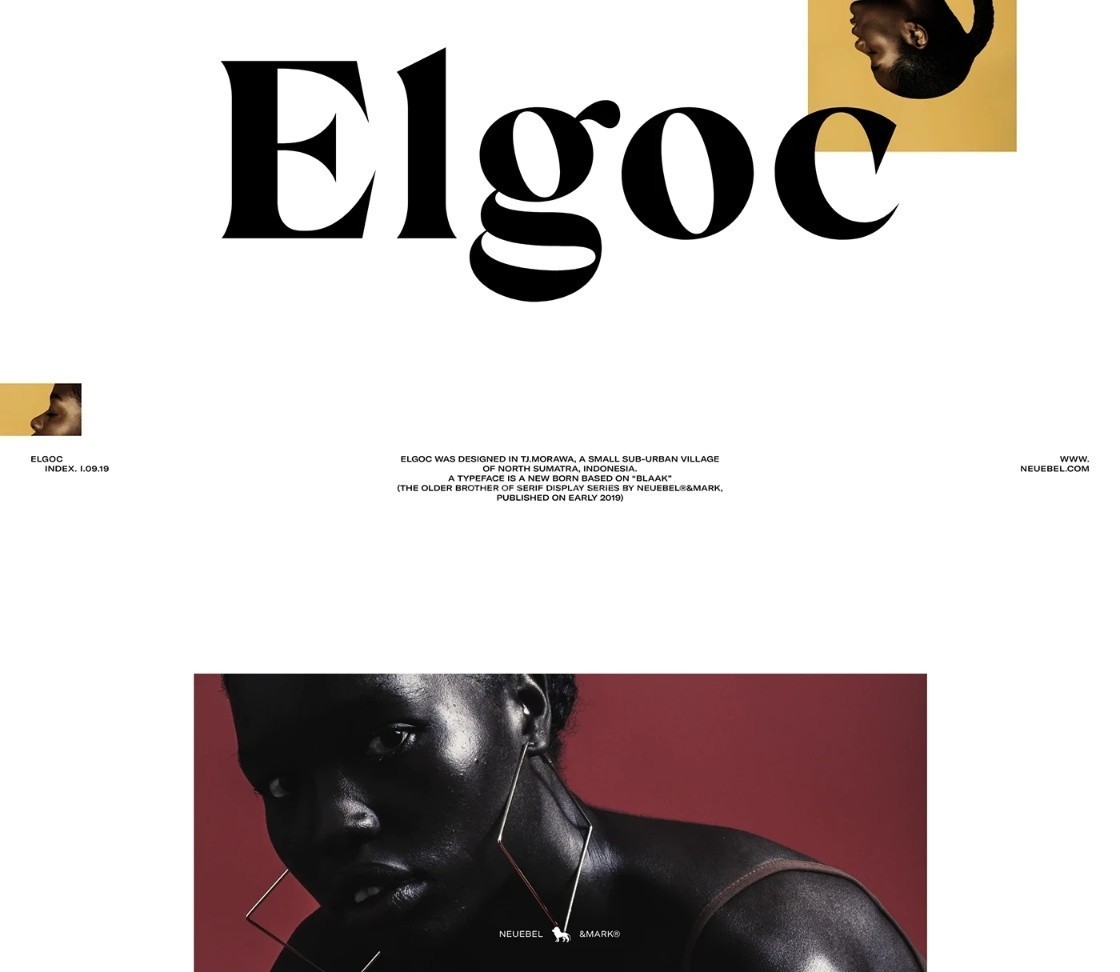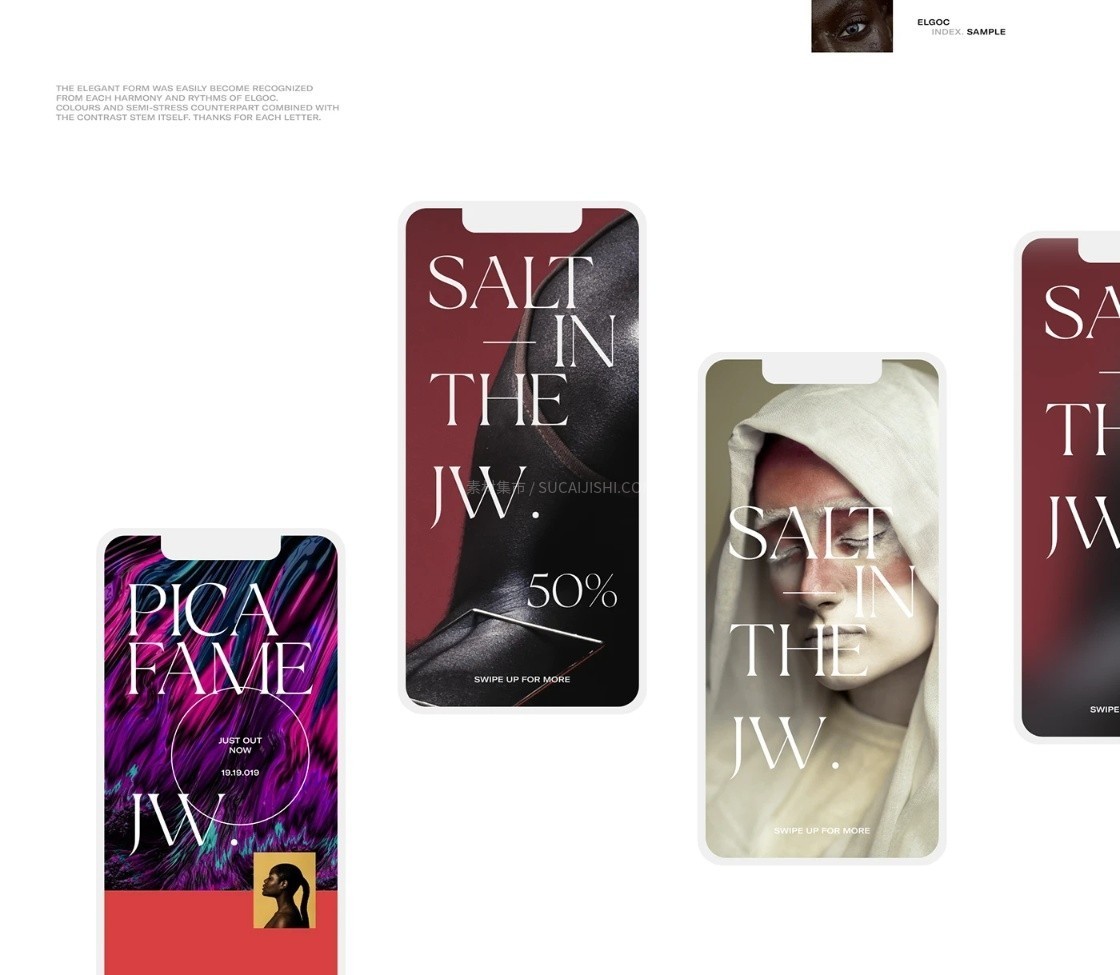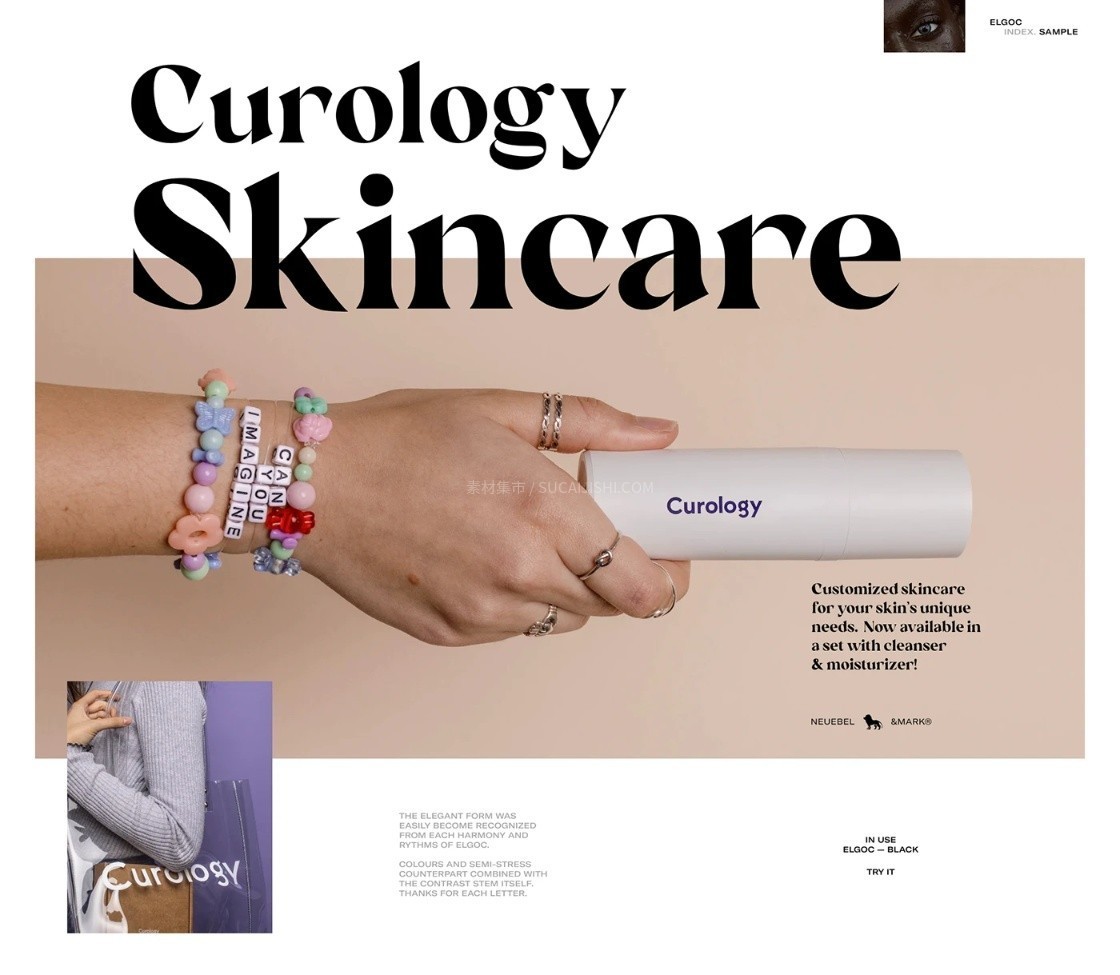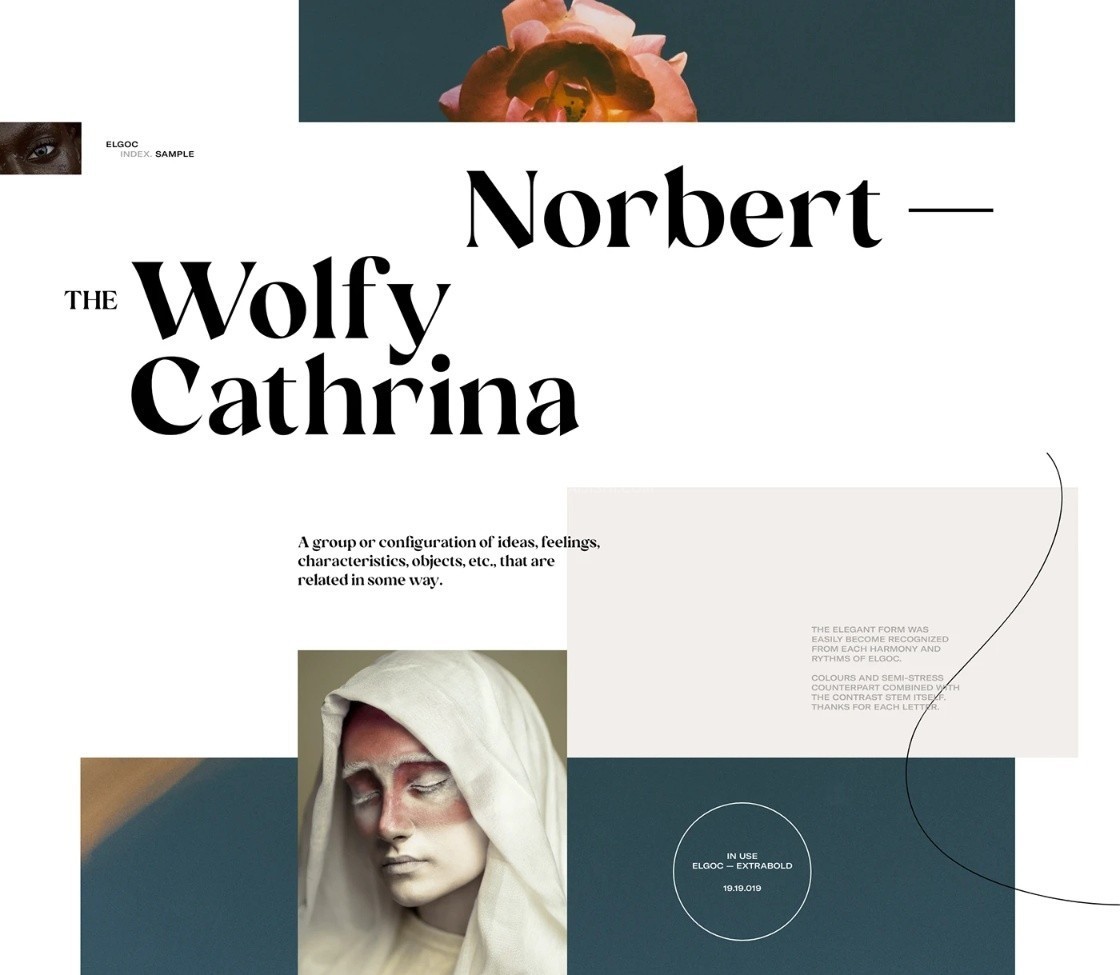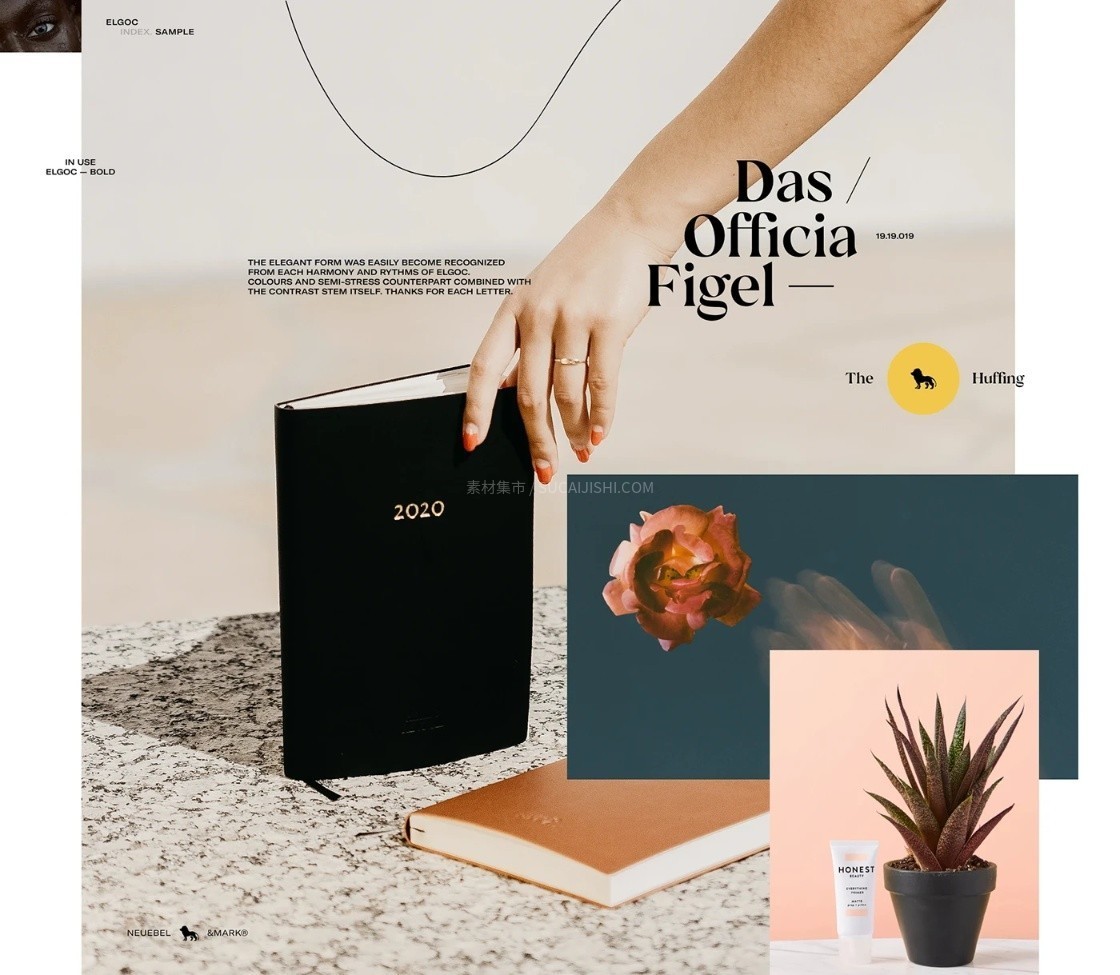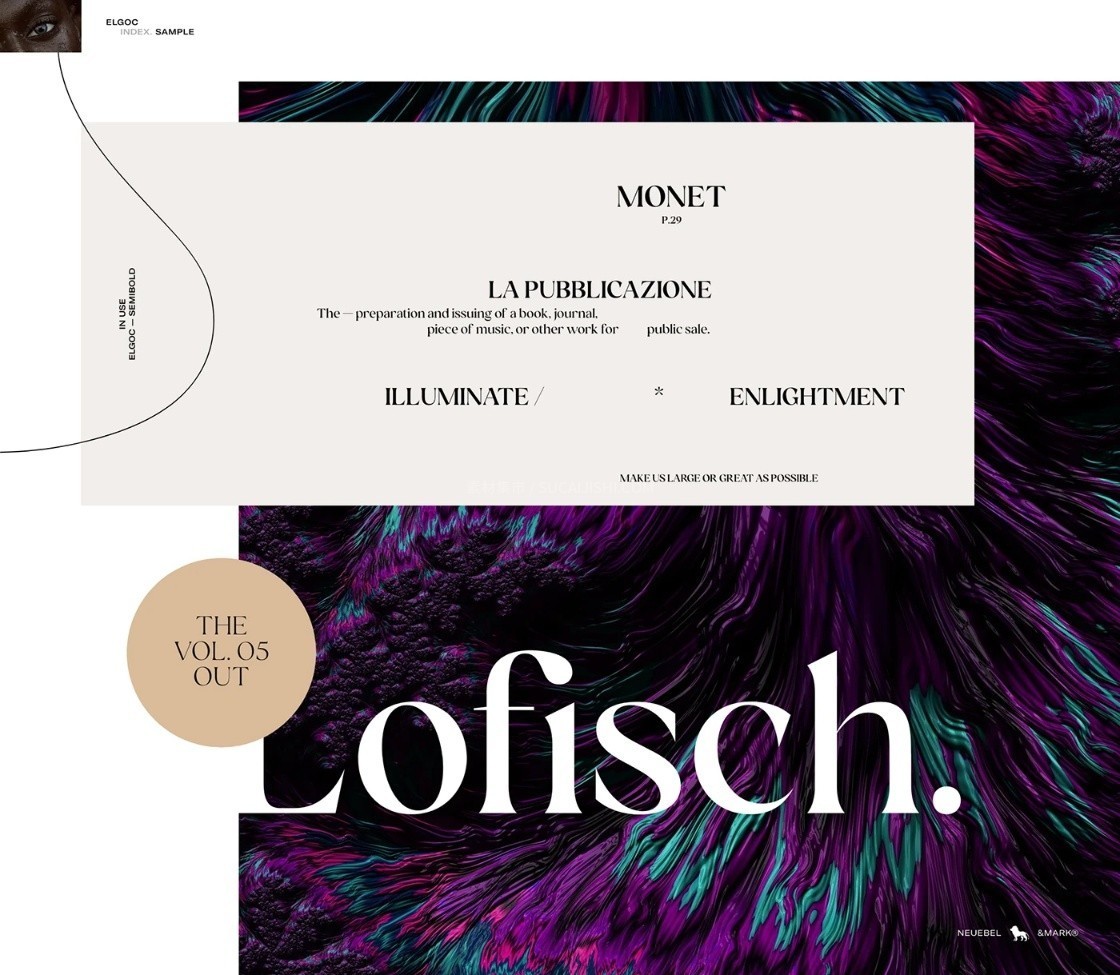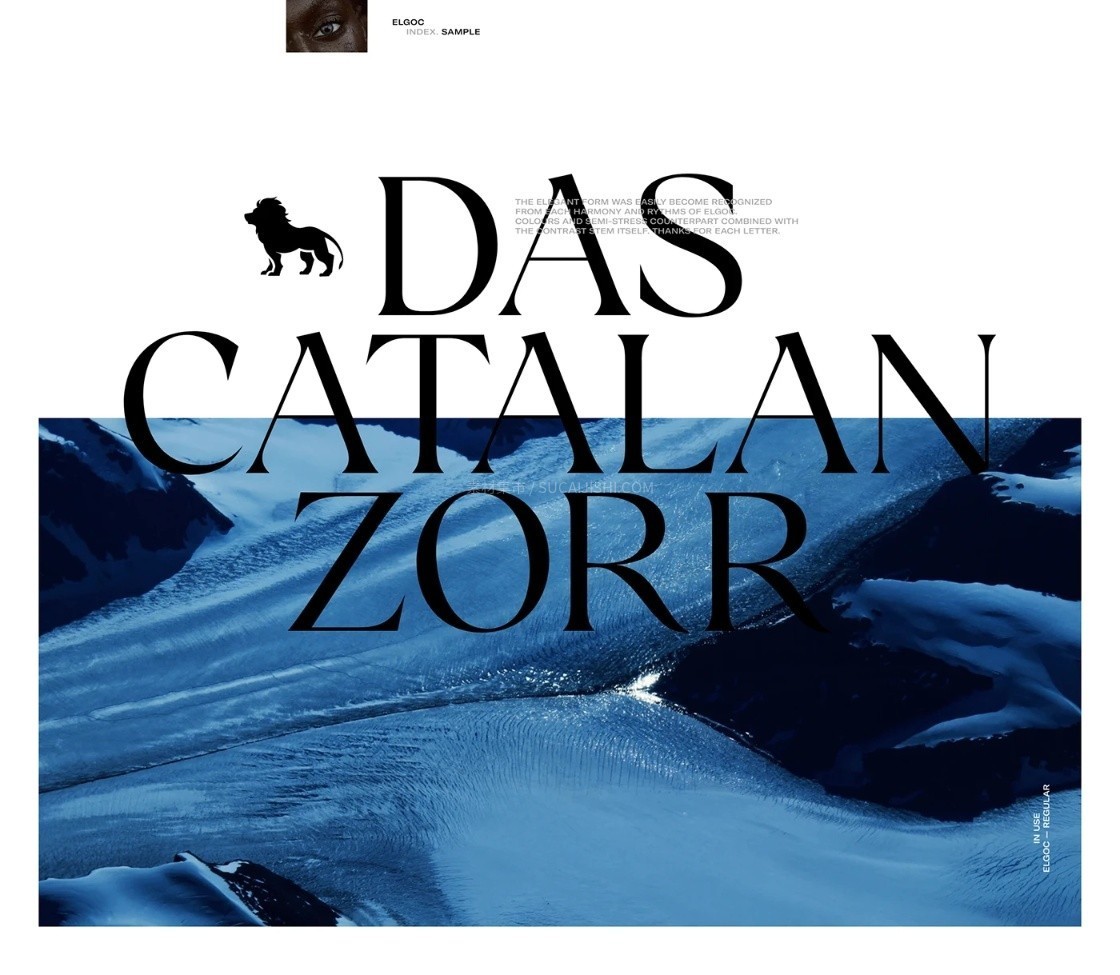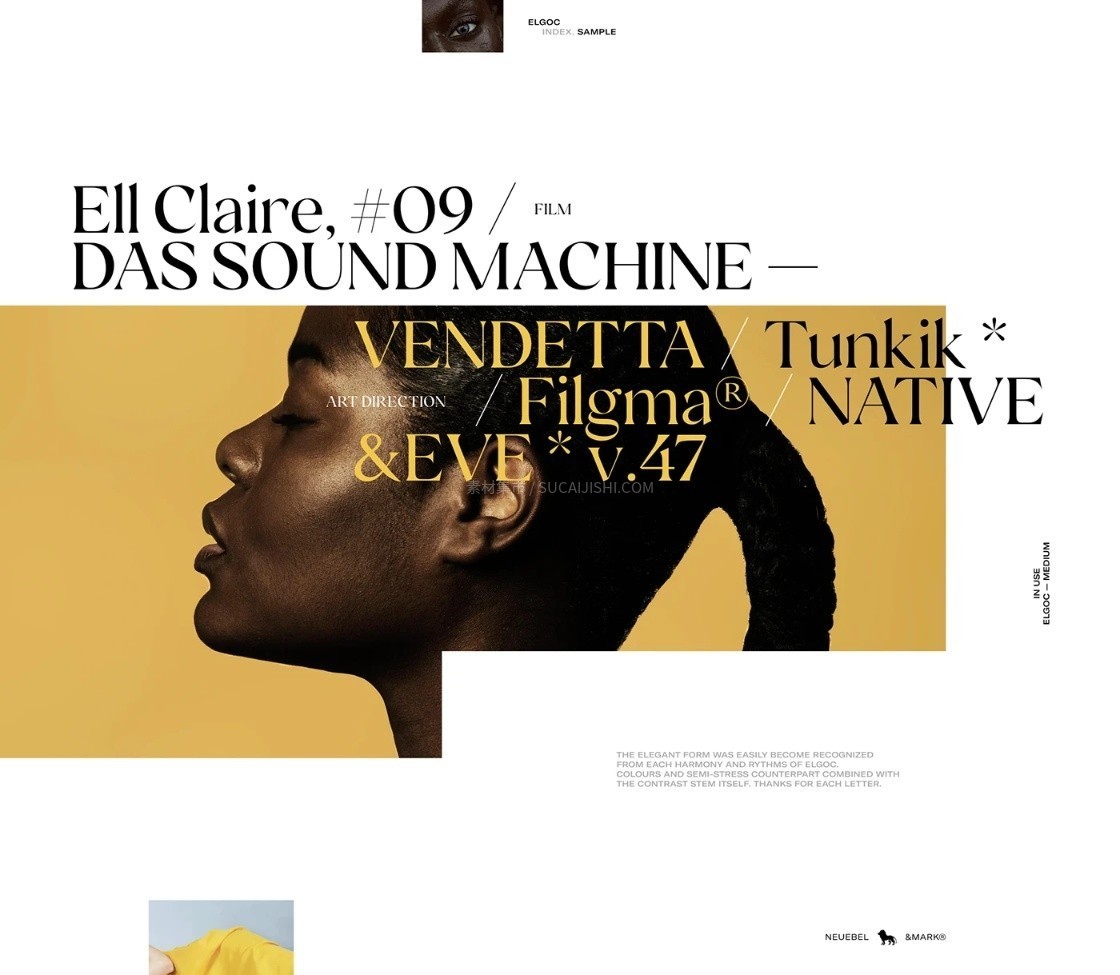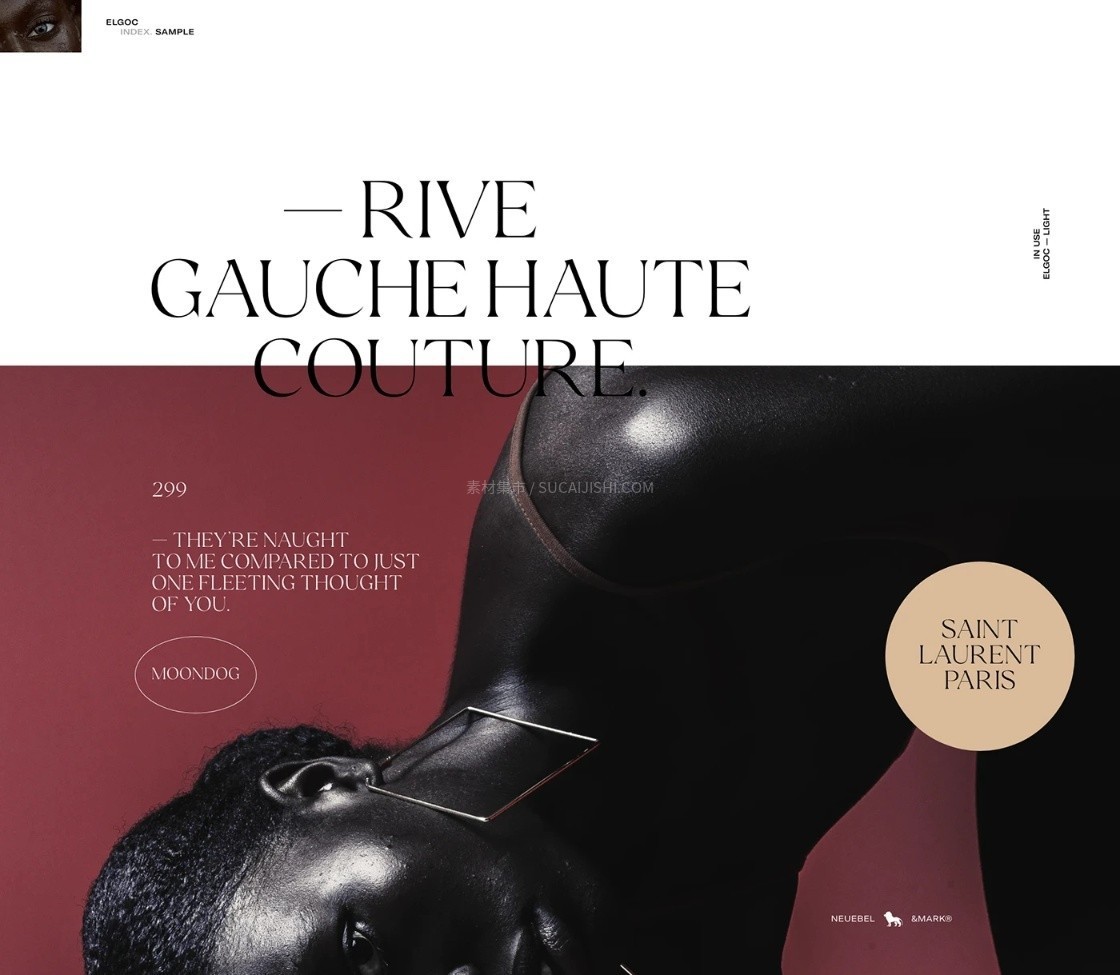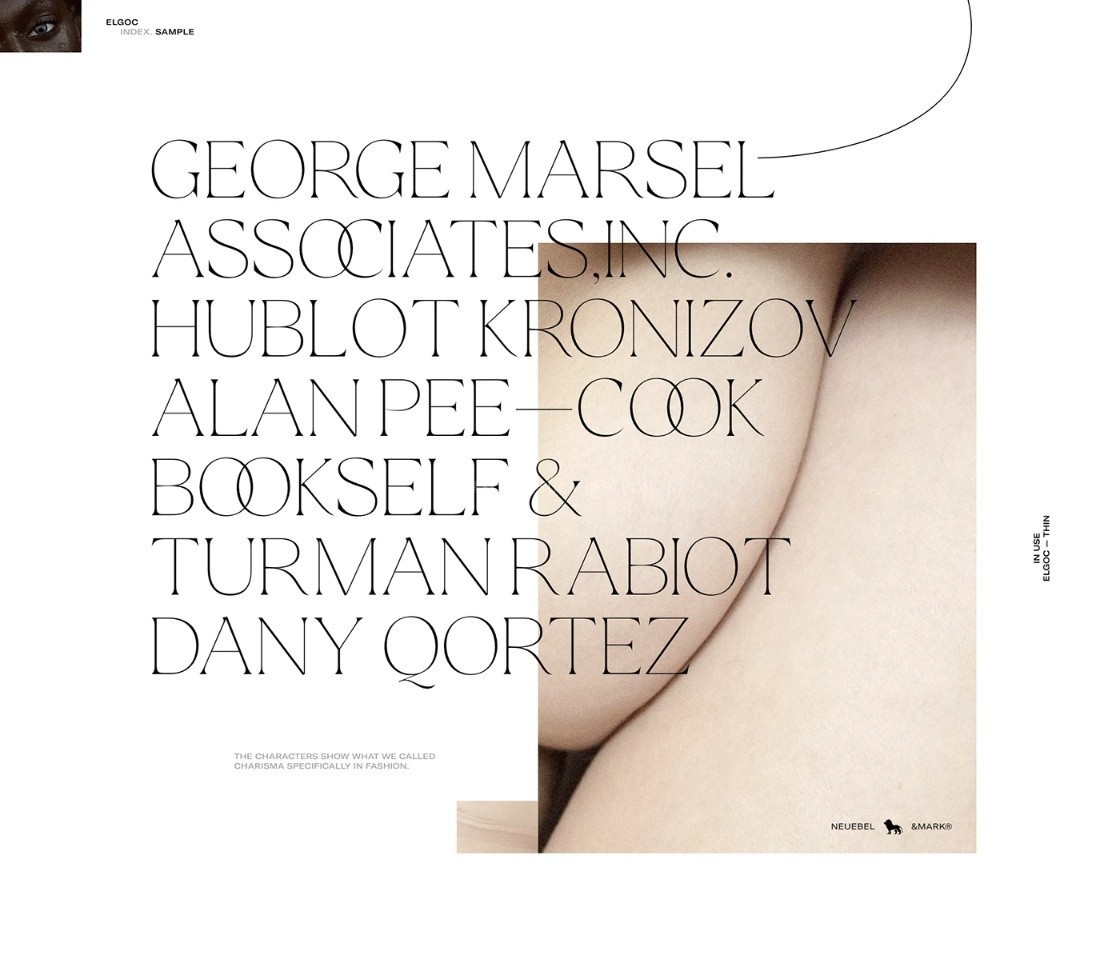
Elgoc 高级优雅衬线字体系列(16种样式)
Elgoc 是一款拥有优美字形、强烈粗细对比度的高级衬线字体。整个字体家族包含标准版(Std)与替换版(Alt)共计16种丰富的样式选项,兼具古典美感与现代张力。它能够完美驾驭多种排版需求,轻松为你的任何编辑作品和视觉设计增添一丝精致、优雅的高级气息。